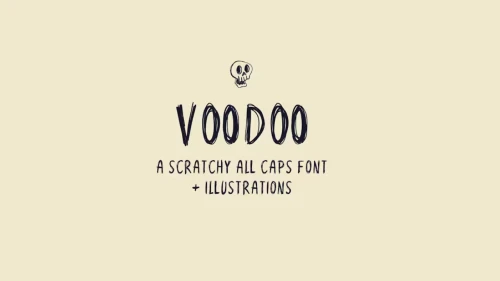
Helloween adalah momen yang sempurna untuk mengekspresikan kreativitas kalian, dan salah satu cara untuk melakukannya adalah melalui pemilihan font yang tepat. Berikut adalah beberapa font yang cocok untuk tema Halloween :
1. Pentacle
Pentacle adalah pasangan font dari Design Surplus dengan lebih dari 130 ikon menakutkan yang terinspirasi dari apotek.
2. Wax Museum
Font seram yang dirancang oleh Dustin Williams ini terinspirasi oleh Museum Lilin Chamber of Horror klasik tahun 70an dan 80an.
3. Witchy
Witchy adalah font skrip kuas yang ditulis tangan oleh Dixie Type Co. Gunakan Witchy untuk undangan pesta Halloween, grafik web, dan dekorasi Halloween lainnya.
4. Moonhells
Moonhells adalah font yang dibuat untuk melengkapi desain apa pun yang terinspirasi Halloween. Font ini memiliki karakter yang kuat dan dilengkapi dengan beberapa tambahan seperti template flyer dan koleksi ikon Halloween!.
5. Scary Skelly Font
Scary Skelly adalah font dekoratif Halloween yang terinspirasi oleh kerangka klasik yang menyeramkan. Masing-masing hurufnya terbuat dari tulang yang digambar tangan, gaya yang berani dan menyenangkan untuk proyek apa pun yang berhubungan dengan hal yang seram.
6. Corpse Bride
Corpse Bride adalah font seram yang dirancang oleh Ulrich Planer dan dipersembahkan oleh Kern Club. Gunakan font ini untuk memberikan tampilan dan nuansa yang sedikit menyenangkan namun menyeramkan.
7. Voodoo
Voodoo adalah font Halloween yang kasar, coretan, dan huruf besar semua, tepat pada saat Anda menjadi seram.